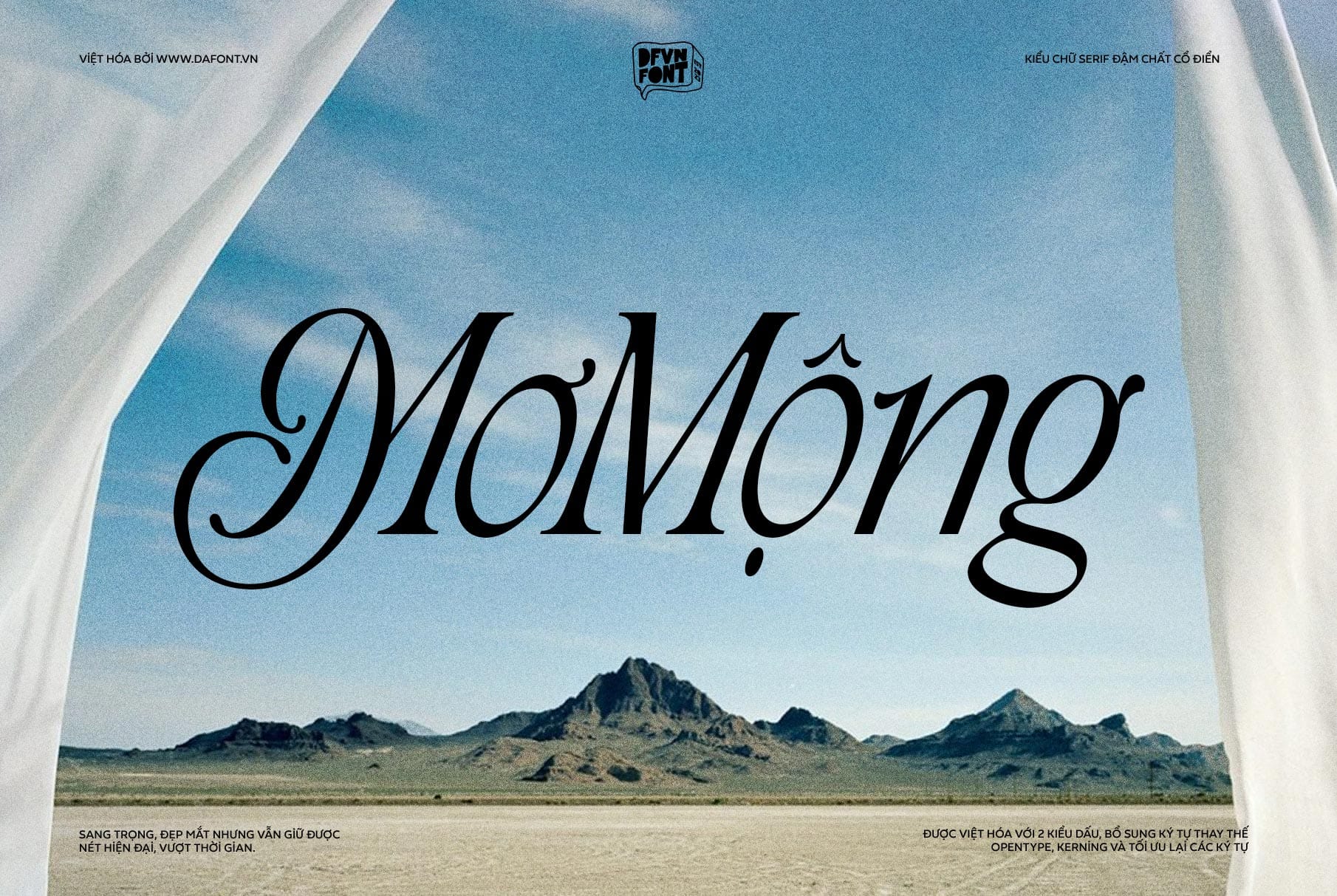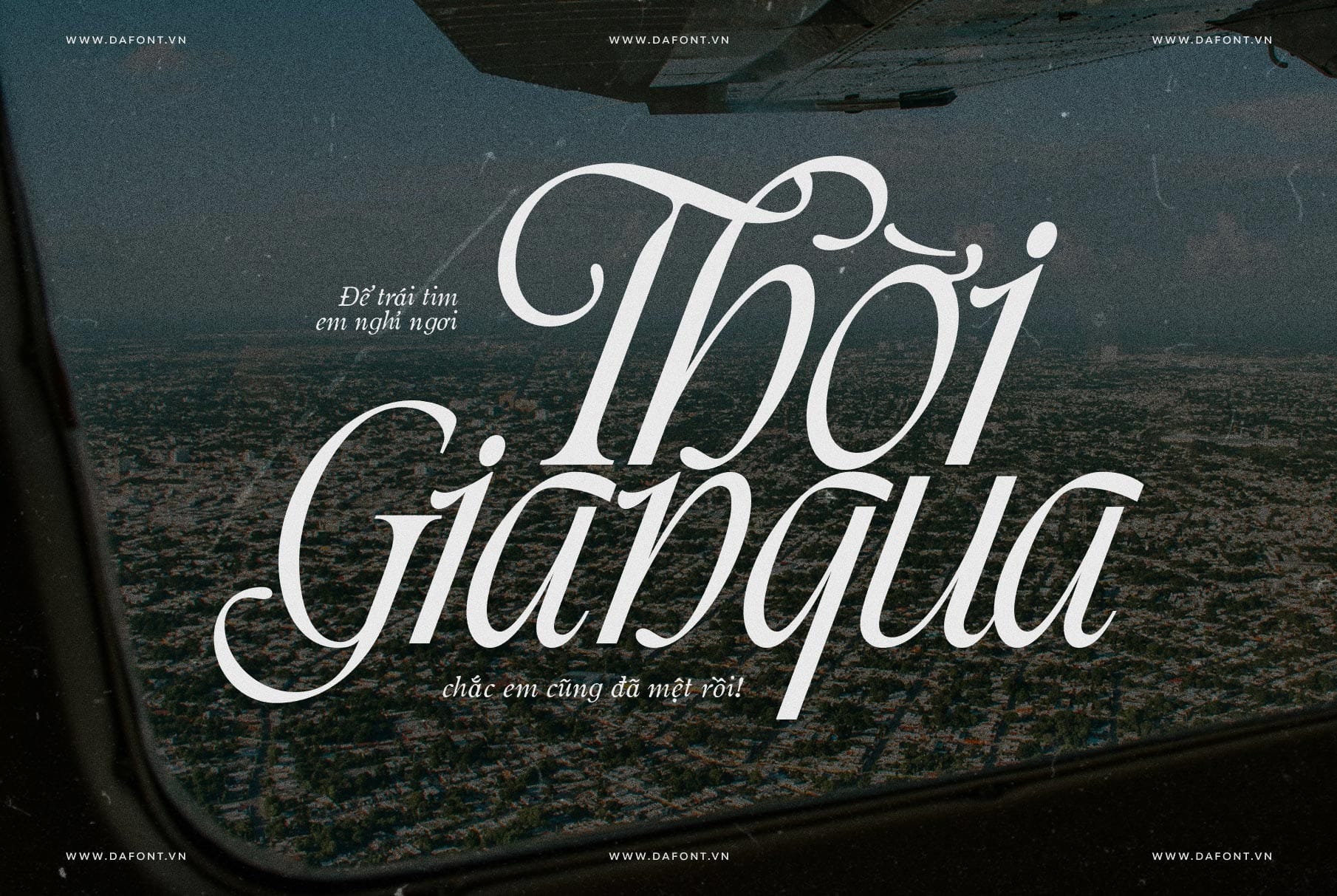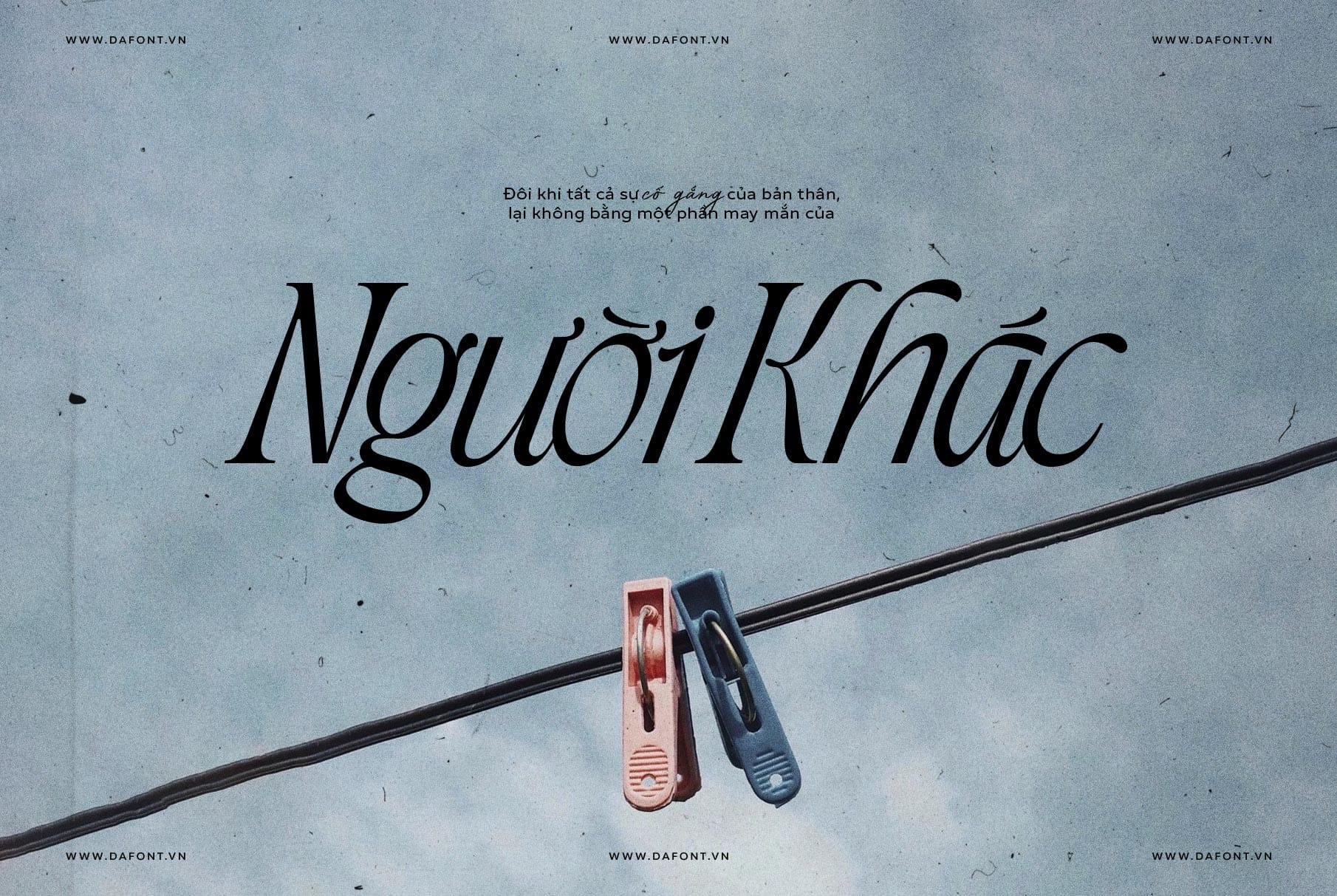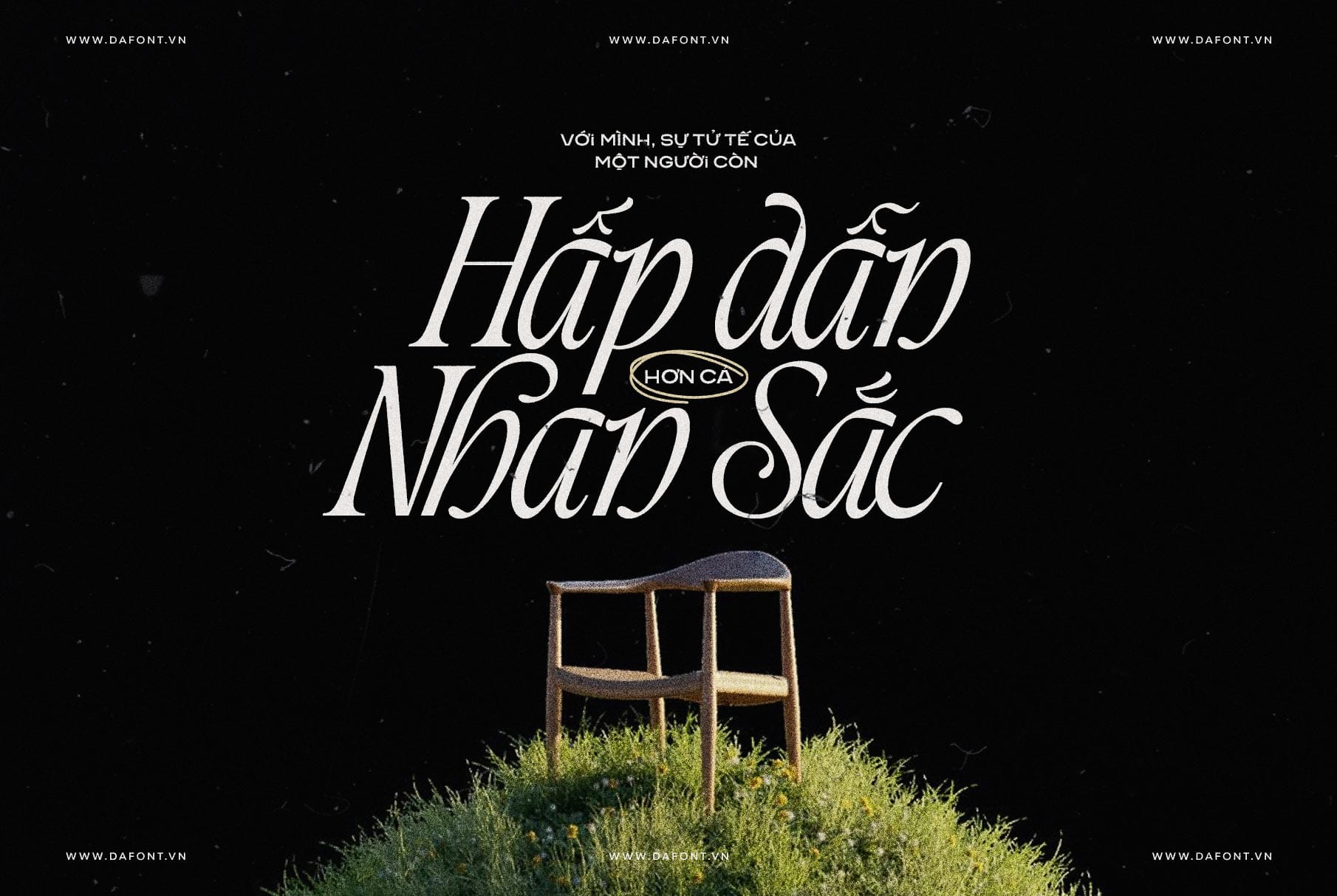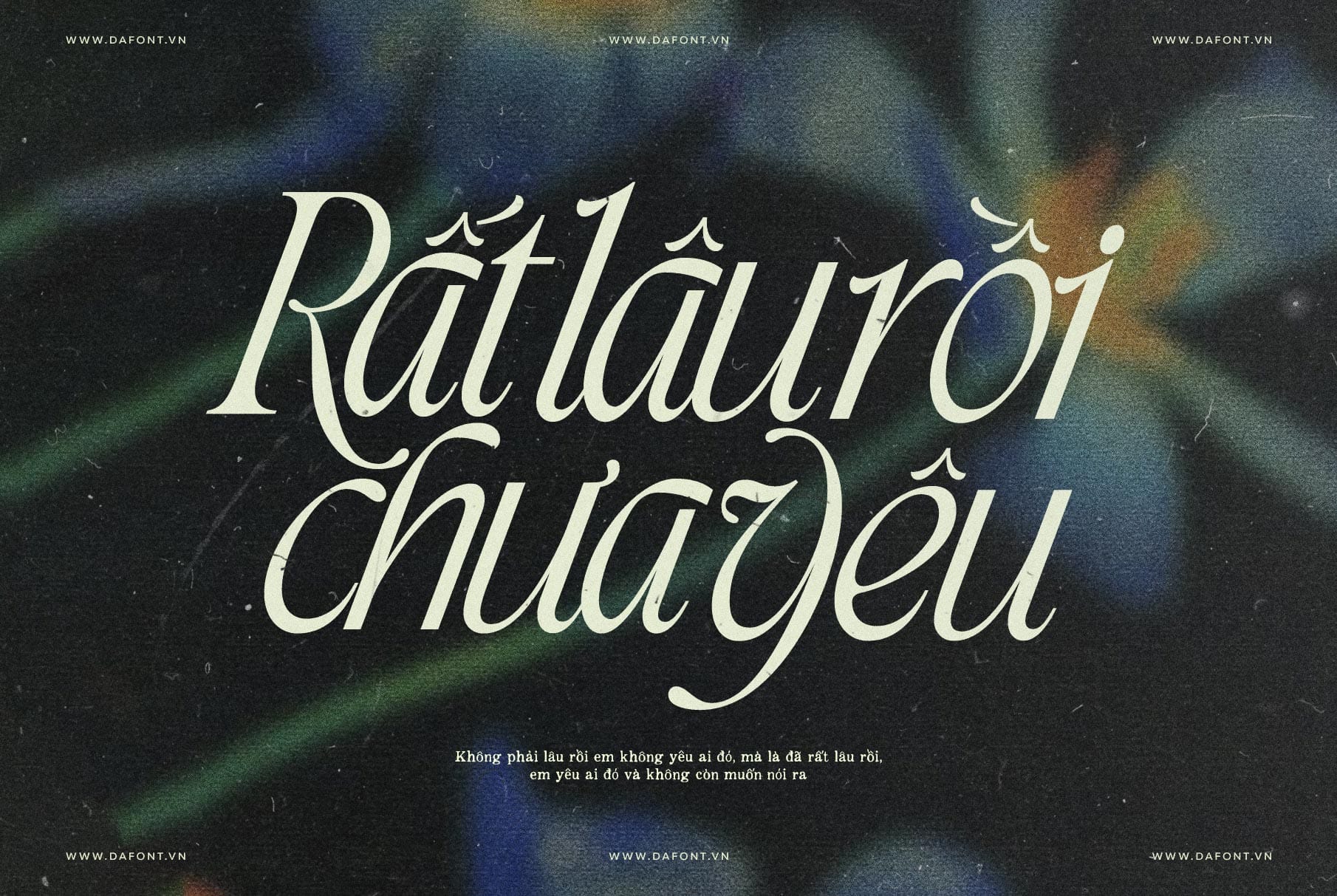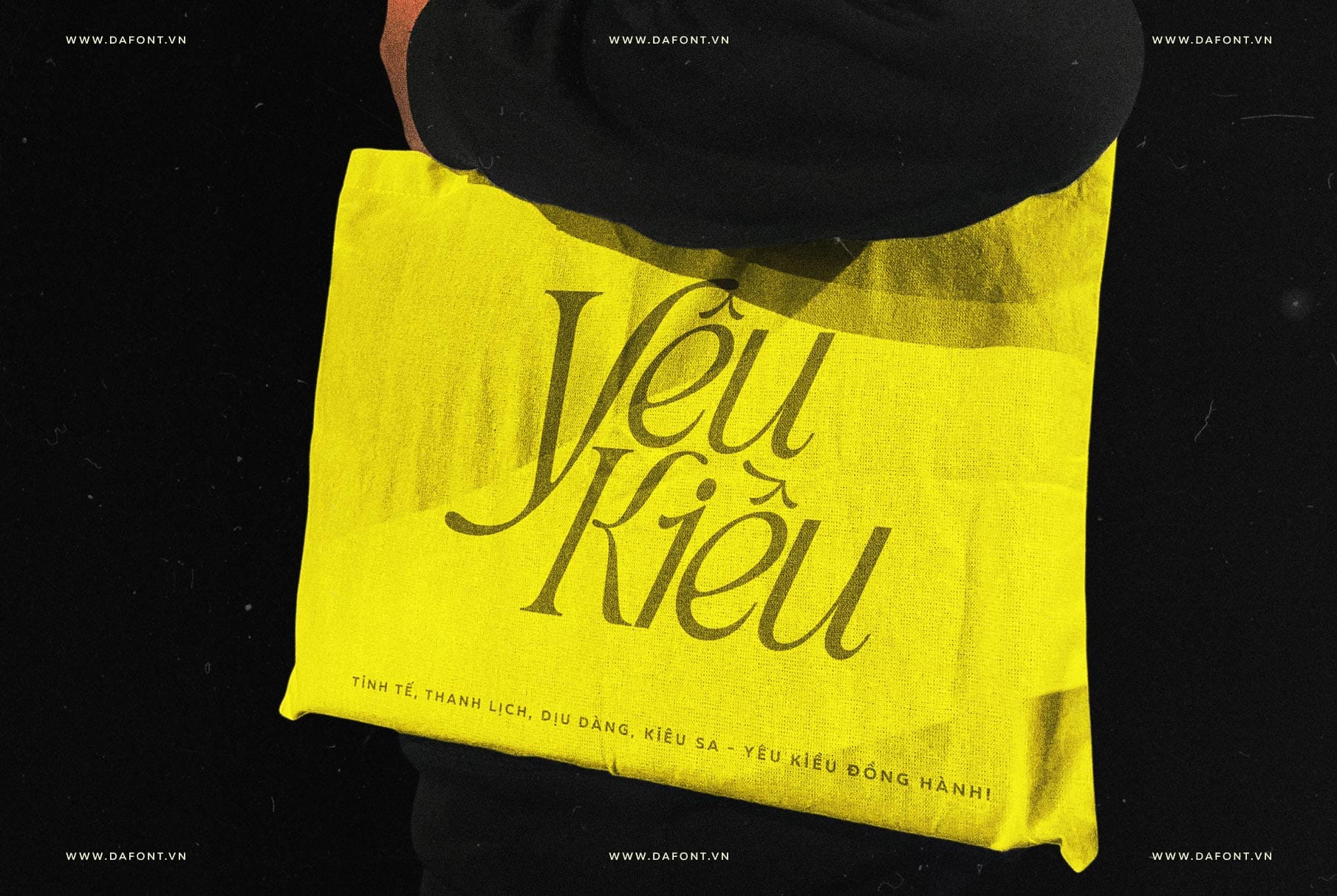
DFVN TAN – THE MYTHS font nổi bật như một sự kết hợp hoàn hảo giữa vẻ đẹp cổ điển của huyền thoại và nét tinh tế của thời đại mới. Đây là lựa chọn lý tưởng cho những ai muốn mang đến hơi thở bí ẩn và cuốn hút vào các dự án sáng tạo của mình.
Nếu bạn đang tìm kiếm một font chữ đậm chất cổ điển, đẹp mắt, các nét chữ được thiết kế uốn lượn độc đáo và đa năng, hãy cùng khám phá DFVN TAN – THE MYTHS qua bài viết này!
DFVN TAN – THE MYTHS – Kiểu chữ nổi bật
TAN – THE MYTHS với các đường nét thanh thoát, chi tiết tinh xảo và phong cách serif đầy cuốn hút, font chữ này gợi lên hình ảnh của những văn bản cổ điển nhưng vẫn giữ được sự hiện đại, dễ ứng dụng. Được thiết kế để trở thành cầu nối giữa quá khứ và hiện tại, TAN – THE MYTHS mang đến cảm giác huyền bí, sang trọng, khiến nó trở thành một typeface thiết kế lý tưởng cho nhiều mục đích sáng tạo.
Dù bạn đang làm việc trên một bìa sách, thiệp cưới, trang web mang hay xây dựng nhận diện thương hiệu nổi bật, DFVN TAN – THE MYTHS font đều có thể đáp ứng hoàn hảo.
Cách sử dụng DFVN TAN – THE MYTHS font hiệu quả
Để tận dụng tối đa vẻ đẹp của font này, dưới đây là một số mẹo hữu ích:
- Kết hợp font: Hãy ghép đôi Tan THE MYTHS với các font sans-serif đơn giản cho phần nội dung chính, để nó tỏa sáng ở tiêu đề hoặc logo.
- Ứng dụng: Sử dụng font này cho các thiết kế như bìa sách, poster, thiệp mời hoặc bất kỳ dự án nào cần phong cách cổ điển hoặc hiện đại.
- Màu sắc và kích thước: Thử nghiệm với màu sắc đậm, sâu (như vàng hoàng gia hoặc xanh ngọc) và kích thước lớn để làm nổi bật các chi tiết tinh tế của font.
Bạn đang tự hỏi font nào tốt nhất cho thiết kế cổ điển? lãng mạn chắc chắn DFVN TAN – THE MYTHS là một ứng cử viên sáng giá mà bạn không thể bỏ qua.
Kết luận
Với sự hòa quyện giữa nét đẹp cổ điển và tính ứng dụng hiện đại, DFVN TAN – THE MYTHS font không chỉ là một kiểu chữ mà còn là cánh cửa dẫn bạn đến những khả năng sáng tạo vô tận. Dù bạn đang kể một câu chuyện về một đám cưới lãng mạn hay xây dựng một thương hiệu thời thượng, font chữ này sẽ giúp bạn tạo nên sự khác biệt.
DFVN TAN – THE MYTHS được Việt hóa tỉ mỉ, ấn tượng với 2 kiểu dấu khác nhau giúp bạn linh hoạt hơn trong thiết kế, các ký tự thay thế cũng được Việt hóa, thêm tính năng stylistic set, kerning đầy đủ và tính năng Opentype cũng được hỗ trợ.